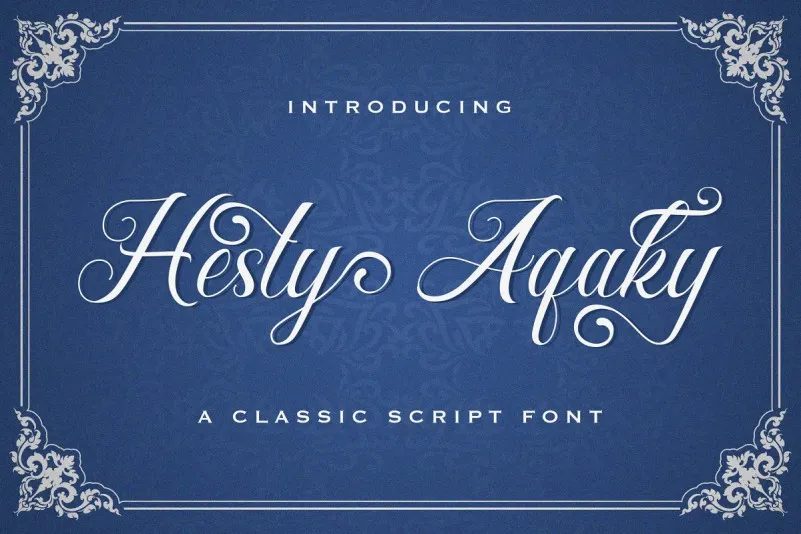
A Hesty Aqaky Font é uma elegante tipografia script que traz um toque relaxado e leve. Feita pelo designer de fontes StringLabs, essa fonte apresenta letras bonitas e bem equilibradas, tornando-a perfeita para adicionar a diversos tipos de projetos. Ela destaca-se como uma opção ideal tanto para designers digitais quanto para aqueles que buscam um touch único em suas criações gráficas. Com essa fonte de letra grossa, seus trabalhos ganharão vida e charme, tornando-as mais memoráveis. É importante lembrar que Hesty Aqaky é uma fonte demo, destinada apenas ao uso pessoal, mas qualquer contribuição é muito apreciada pelos criadores da fonte.